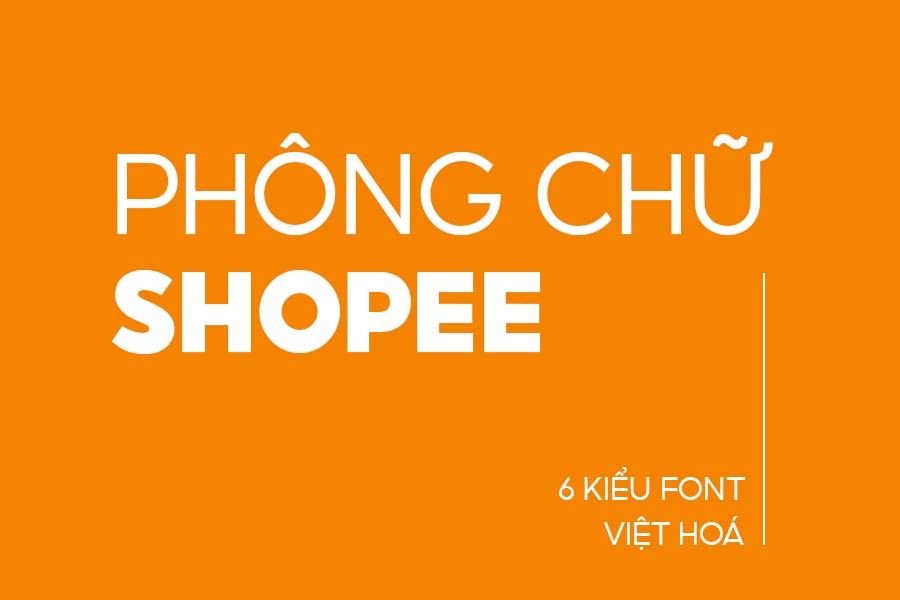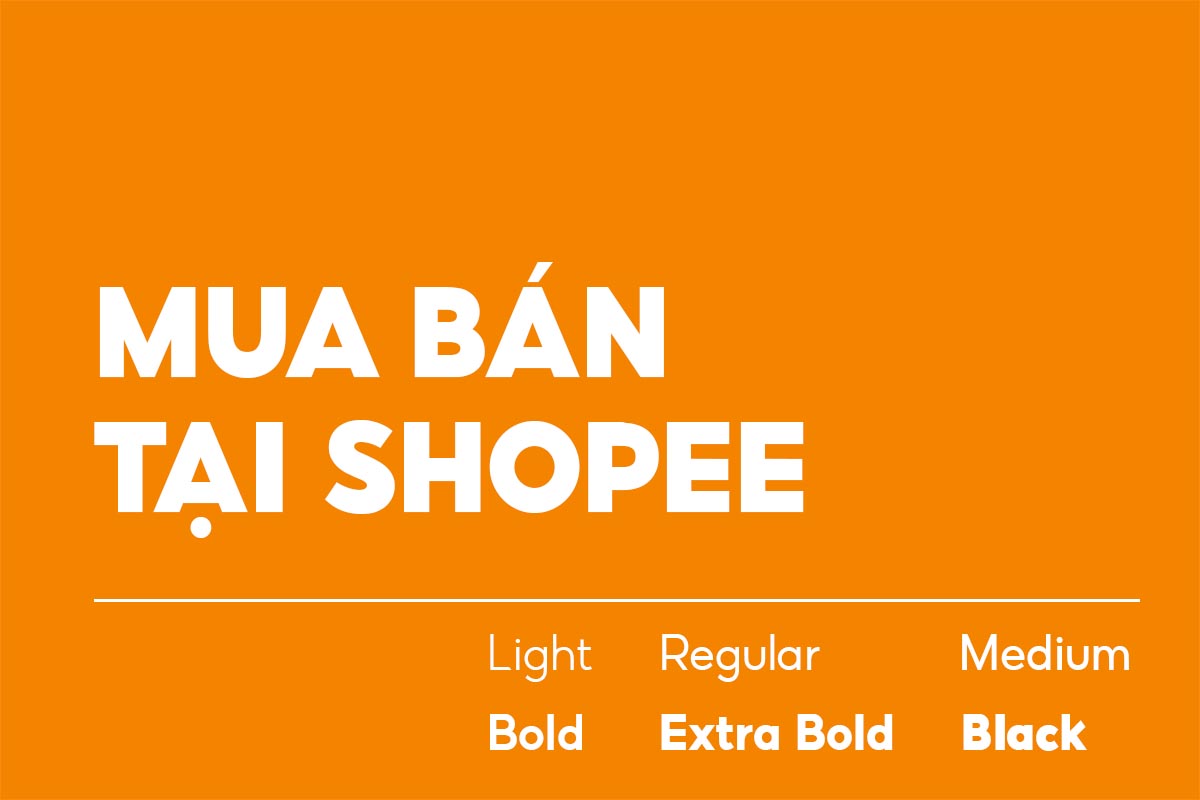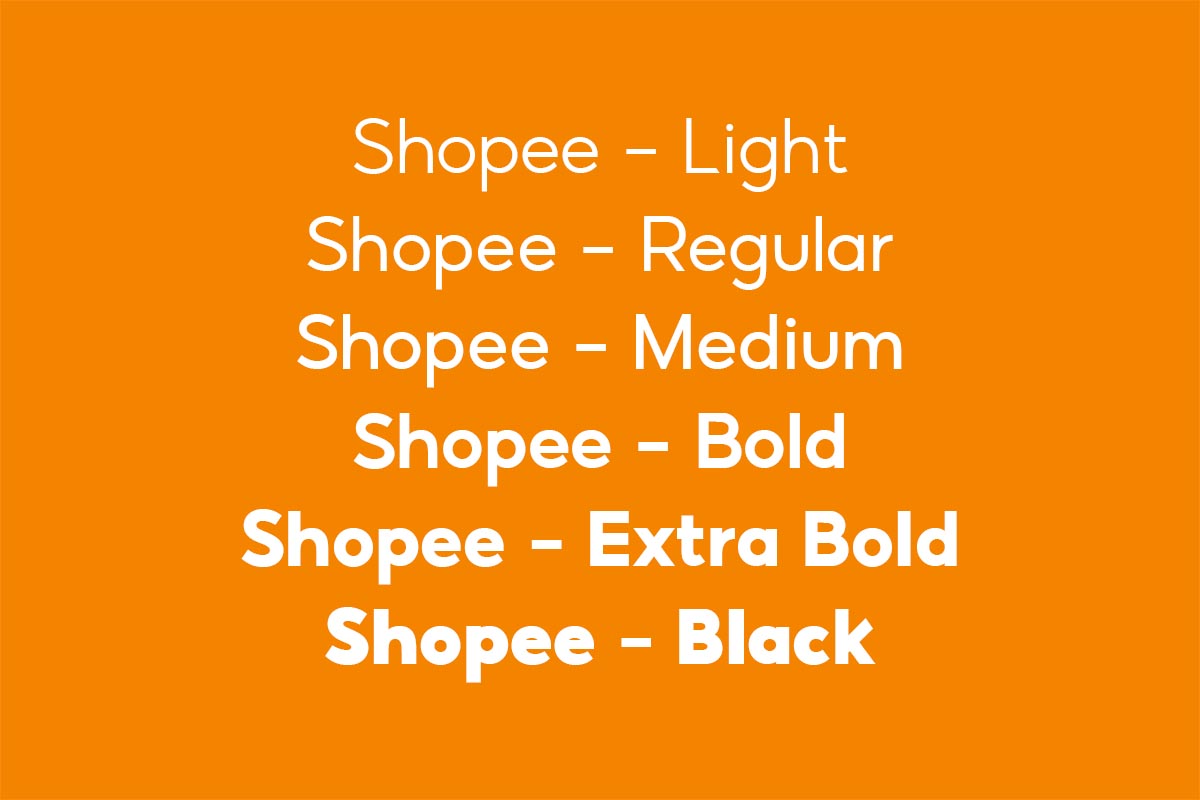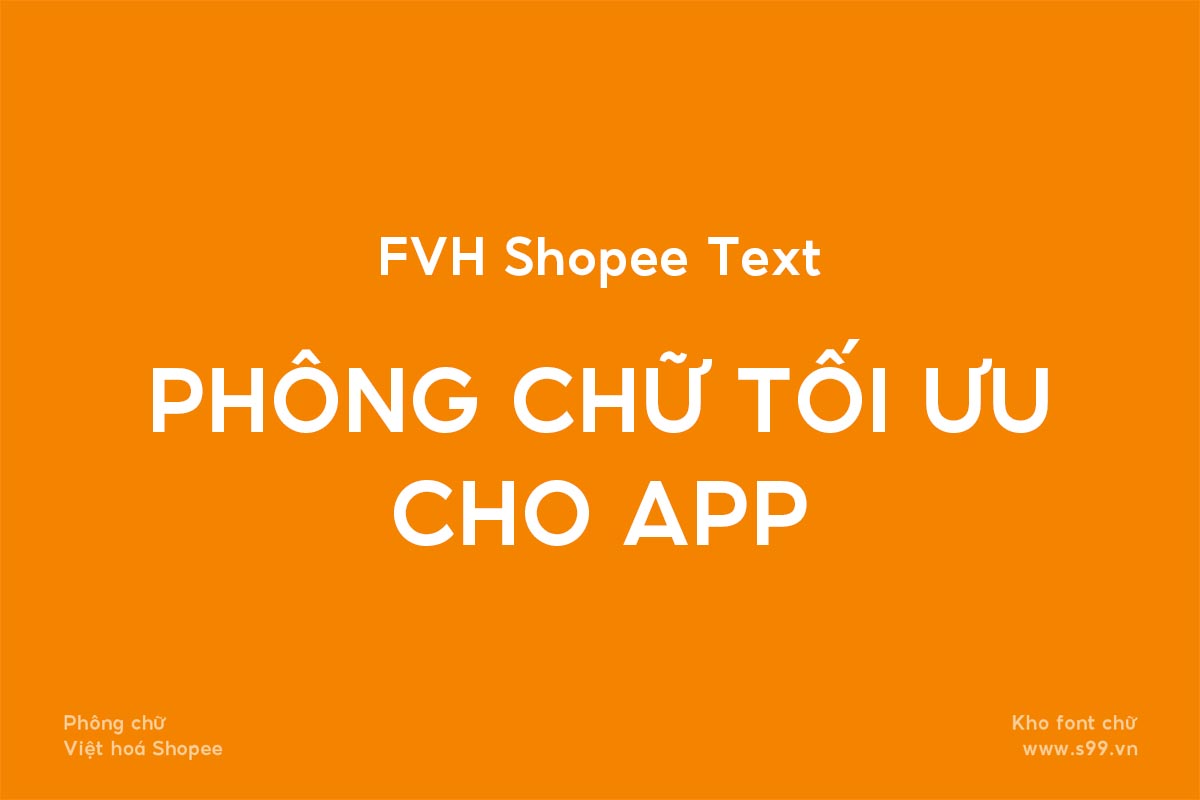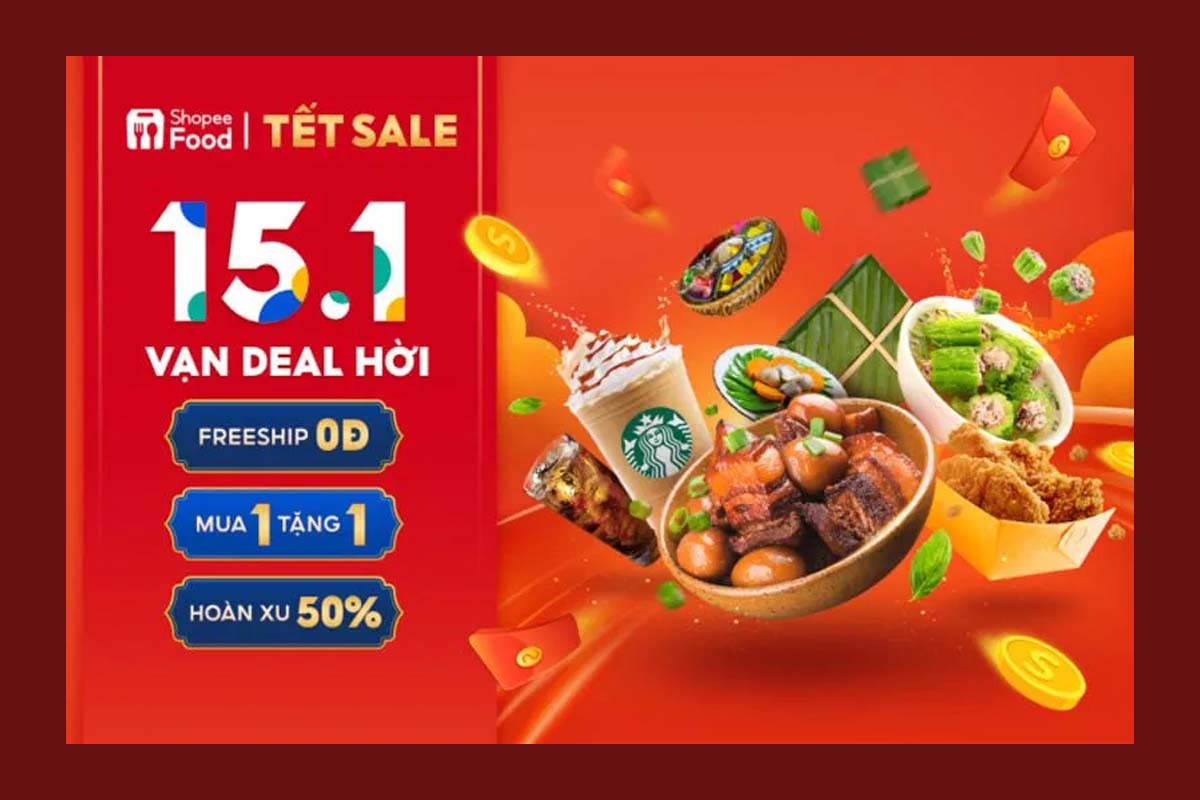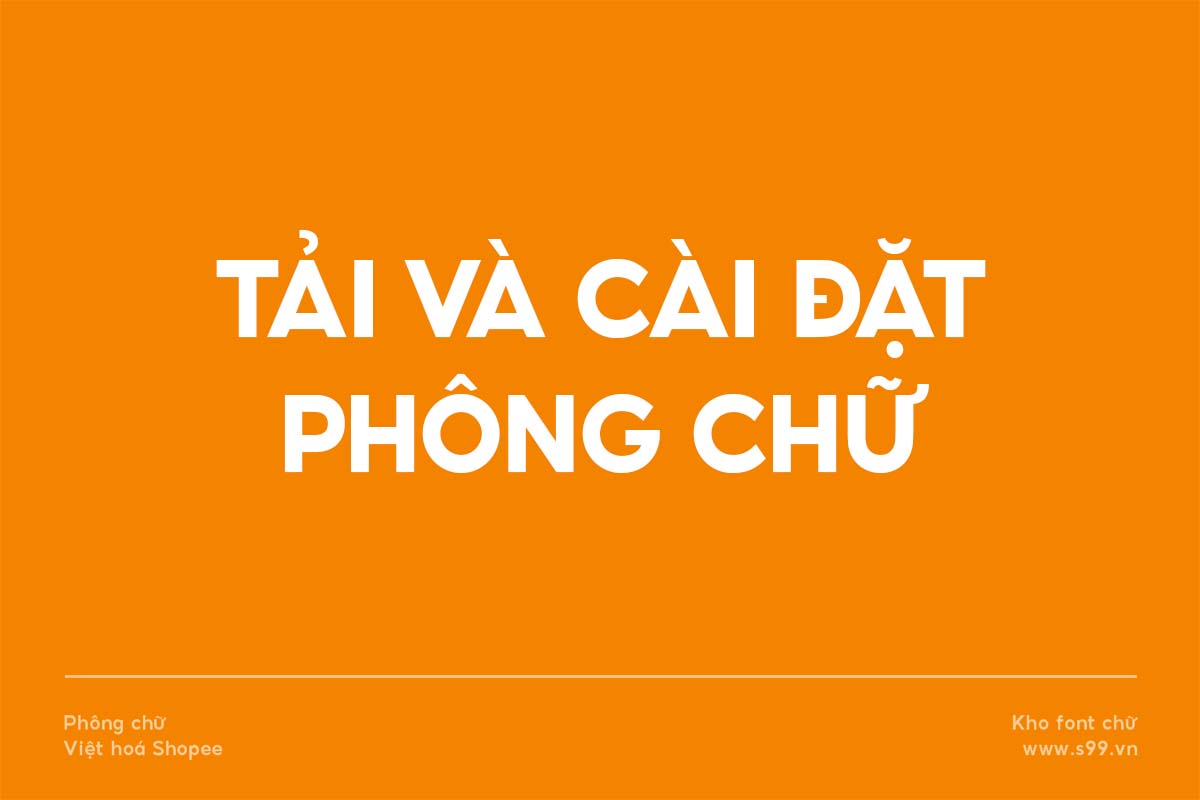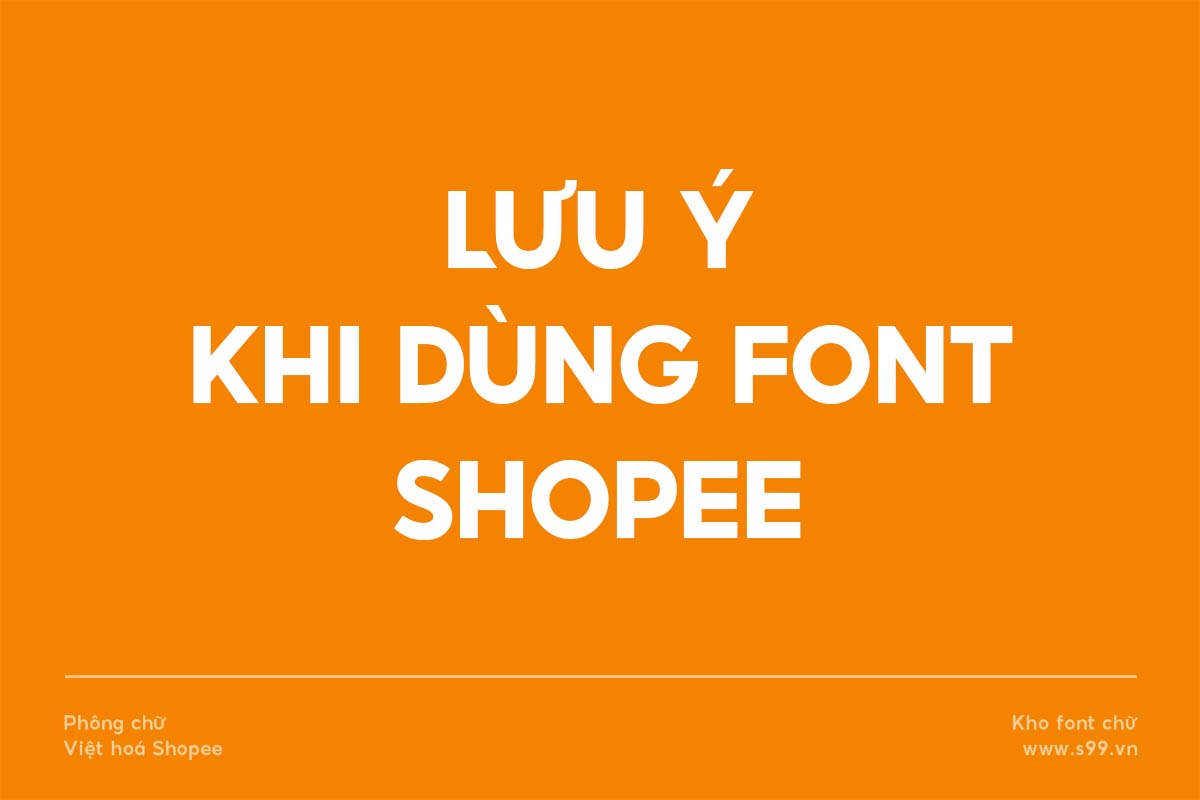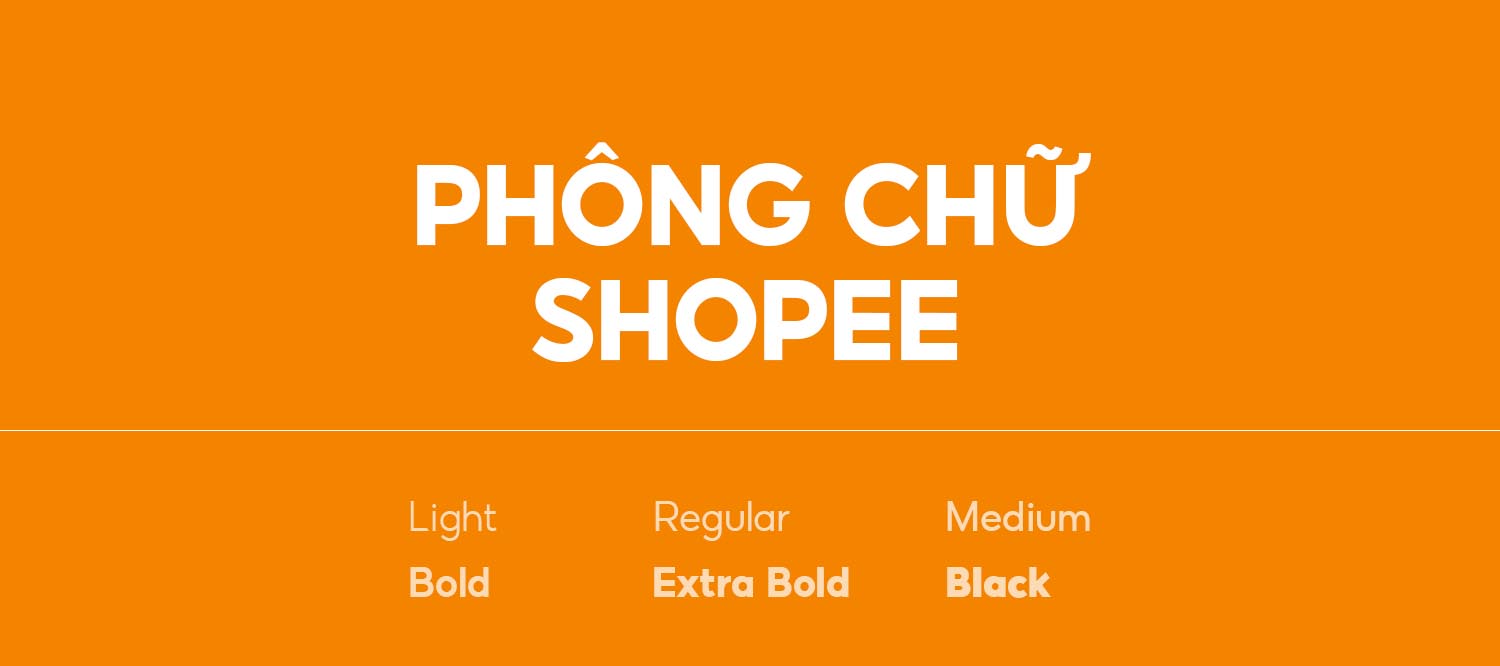
Trong thế giới thiết kế hiện đại, font chữ không chỉ là công cụ trình bày mà còn là yếu tố định hình thương hiệu. Một trong những bộ font được săn đón nhất hiện nay là “font Shopee” kiểu chữ quen thuộc từ nền tảng thương mại điện tử hàng đầu Đông Nam Á. Nhiều designer, marketer và chủ shop online đang tìm kiếm bộ font này để tạo sự chuyên nghiệp, tin cậy và thu hút trong từng thiết kế. Bài viết dưới đây sẽ cung cấp đầy đủ thông tin và hướng dẫn để bạn tải và sử dụng bộ font Shopee tiếng Việt một cách dễ dàng và hiệu quả nhất.
Font Shopee thường được hiểu là kiểu chữ mô phỏng phong cách thiết kế đặc trưng của Shopee thương hiệu dẫn đầu trong lĩnh vực thương mại điện tử. Điều khiến nó trở nên phổ biến không chỉ nằm ở hình thức đơn giản, hiện đại mà còn ở cảm giác tin cậy mà người dùng Việt đã quen thuộc khi lướt Shopee mỗi ngày. Khi áp dụng font này vào các banner khuyến mãi, hình ảnh sản phẩm hay bài đăng mạng xã hội, bạn đang tạo một liên tưởng tích cực đến trải nghiệm mua sắm thân quen và đáng tin.
Bộ font Shopee Display tiếng Việt hiện đang được Việt hóa và phân phối miễn phí dưới 6 kiểu chữ: Light, Regular, Medium, SemiBold, Bold và Black. Mỗi kiểu mang một trọng lượng và sắc thái khác nhau, cho phép người dùng linh hoạt trong bố cục thiết kế. Không chỉ hỗ trợ đầy đủ bộ dấu tiếng Việt, bộ font này còn giữ được nét mạnh mẽ, sạch sẽ và cân đối so với bản gốc. Phiên bản Việt hóa hiện có thể sử dụng ổn định trên cả phần mềm thiết kế chuyên nghiệp và các nền tảng online như Canva, CapCut.
Shopee Display Light là lựa chọn hoàn hảo cho những phần nội dung nhẹ, phụ đề hoặc chú thích nhỏ, khi bạn muốn giữ cho thiết kế thoáng đãng và không quá nặng nề. Trong khi đó, Regular đóng vai trò là kiểu chữ tiêu chuẩn, dễ đọc và hài hòa – thích hợp để trình bày đoạn văn chính.
Nếu bạn cần nhấn mạnh tiêu đề hoặc tạo điểm nhấn nhẹ, hai kiểu Medium và SemiBold sẽ phát huy tác dụng. Với các chương trình khuyến mãi lớn, tiêu đề đậm, thu hút thị giác thì hai biến thể mạnh nhất là Bold và Black sẽ là sự lựa chọn không thể thiếu. Nhìn chung, bộ font được thiết kế để dễ dàng điều chỉnh theo từng mục đích hiển thị.
Khác với Shopee Display, font FVH Shopee Text là một biến thể dành riêng cho việc hiển thị văn bản trong giao diện ứng dụng. Thiết kế của nó tối ưu hóa độ nét ở kích thước nhỏ và trên màn hình điện thoại, đảm bảo người dùng không bị mỏi mắt khi đọc nội dung dài. Đây là font phù hợp khi bạn cần trình bày mô tả sản phẩm, thông tin trong app, hoặc soạn nội dung bài viết dài có độ nhận diện thương hiệu Shopee.
Với những ưu điểm kể trên, font Shopee được ứng dụng rộng rãi trong thiết kế banner giảm giá, poster quảng cáo, landing page sản phẩm, hay thậm chí là các mẫu slide trình bày cho doanh nghiệp thương mại điện tử. Không ít người dùng còn áp dụng bộ font này để làm thumbnail cho video YouTube, TikTok theo chủ đề flash sale – giúp nội dung nổi bật hơn và dễ dàng tạo liên tưởng đến Shopee trong tâm trí người xem.
Font Shopee không chỉ là một kiểu chữ, mà còn là công cụ thiết kế hiệu quả cho những ai muốn tái hiện phong cách thương mại điện tử hiện đại, gần gũi và hiệu quả tại Việt Nam. Với khả năng trình bày rõ ràng, hỗ trợ đầy đủ tiếng Việt và tính ứng dụng cao, đây là bộ font xứng đáng có mặt trong bộ sưu tập của bất kỳ designer, marketer hay nhà bán hàng nào.